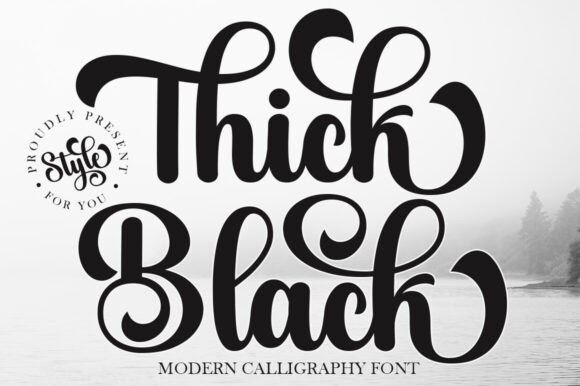
Thick Black
Une police de caractères élégante et raffinée : Thick Black
Thick Black est une police de caractères qui allie douceur et élégance avec une grâce naturelle. Son style féminin et ses traits fluides en font un choix idéal pour des projets créatifs exigeants. Que vous travailliez sur un branding sophistiqué, des invitations de mariage, ou des étiquettes uniques, cette police apporte une touche d’originalité et de raffinement.
Applications variées de Thick Black
- Branding et identité visuelle
- Titres et en-têtes de sites web
- Designs pour mariages et événements spéciaux
- Création de logos et de signes publicitaires
- Étiquettes et emballages personnalisés
Pourquoi choisir Thick Black ?
Cette police se distingue par ses traits épais et harmonieux, qui captent immédiatement l’attention sans agressivité. Son style féminin et moderne la rend parfaite pour des projets où la subtilité et la puissance visuelle sont essentielles. Thick Black s’adapte à tous les supports, qu’il s’agisse d’impression ou de numérique.
Avantages de Thick Black
- Design unique et mémorable